ஸ்டைலான எழுத்துக்கள்!
இந்த உலகில் சொற்களை விட எழுத்துக்களுக்கு வலிமை அதிகம் என்பார்கள் அந்த அளவிற்கு இங்கு எழுத்துக்கள் நிறை சாதித்து இருக்கின்றன.
சரி, பாஸ் உங்களோட கம்பியூட்டர்ல ஒரோ பான்ட்(Fonts) ல எழுதி எழுதி உங்களுக்கு போர் அடிக்குதா.
அப்படினைா ஸ்டைலான பான்ட் களை நீங்கள் தேடுவீர்கள் இதோ அதுக்காகவே இங்கு சில ஸ்டைலான பான்ட்கள் உள்ளன பாஸ்.
இந்த ஸ்டைலான பான்ட்களை பாருங்க பாஸ்....
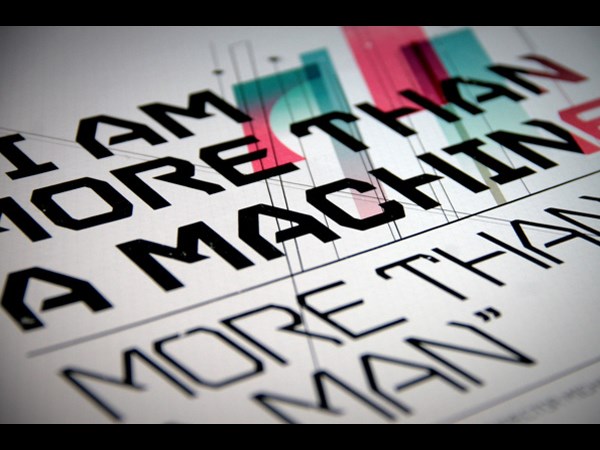
ஸ்டைலான எழுத்துக்கள்!
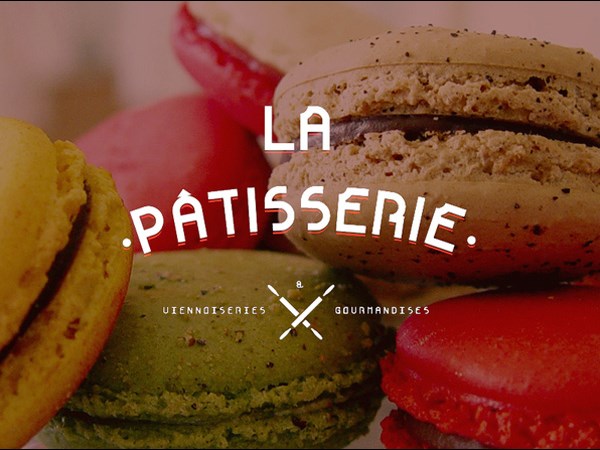
ஸ்டைலான எழுத்துக்கள்!
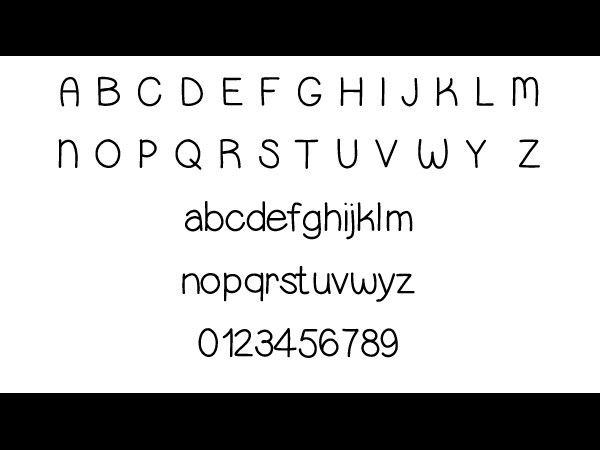
ஸ்டைலான எழுத்துக்கள்!
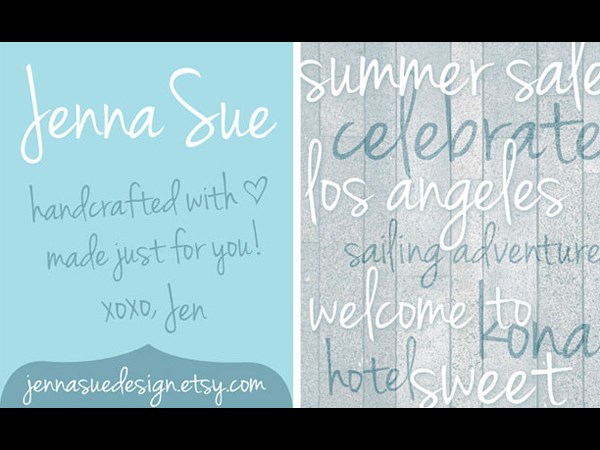
ஸ்டைலான எழுத்துக்கள்!
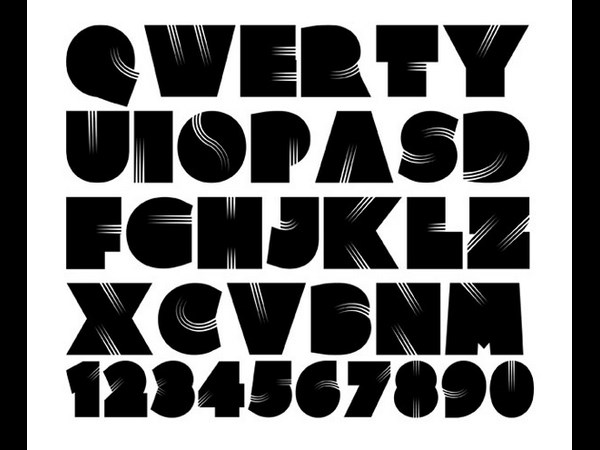
ஸ்டைலான எழுத்துக்கள்!
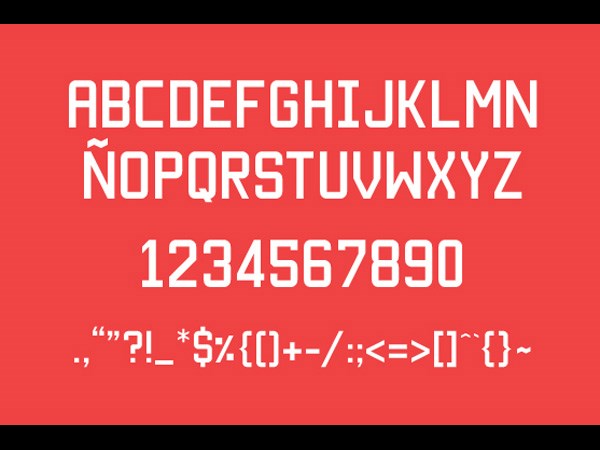
ஸ்டைலான எழுத்துக்கள்!